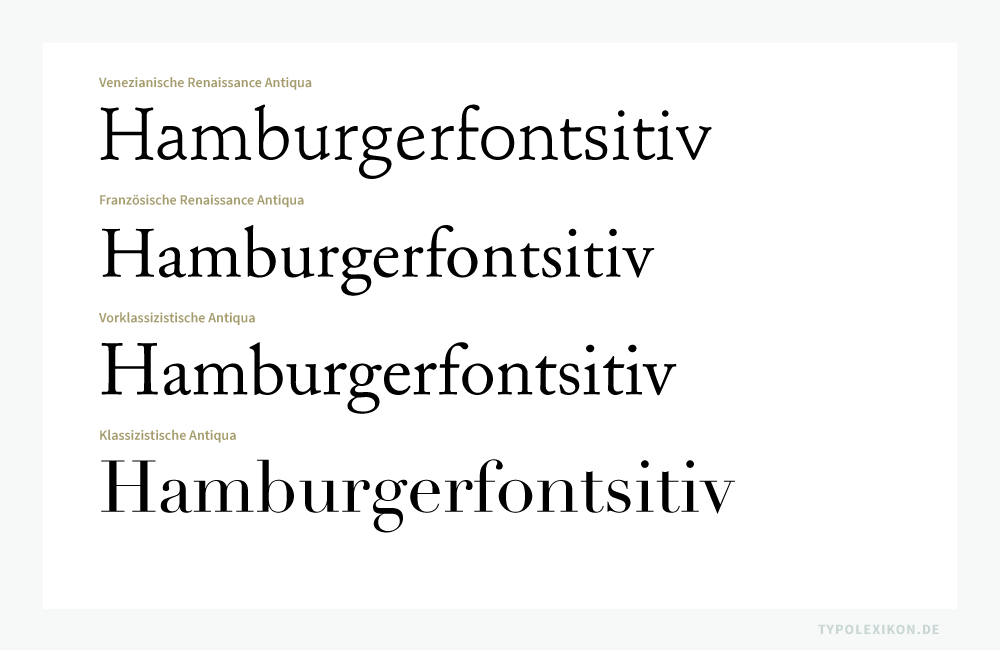
Schriftklassifikation
»Schriftklassifikation« ist ein Terminus aus der Typografie und der Paläografie. Sie dient dem Ordnen, dem Katalogisieren und der Pflege von Schriften in Schriftenbibliotheken sowie dem Studium von Schriften. Klassifikations- und Ordnungsmodelle optimieren spürbar typografische Gestaltungs- und Arbeitsprozesse, also den typografischen Workflow vom Entwurf bis zur Produktion.
Neben philologischen Klassifikationsmodellen existieren für Druckschriften römischen Ursprungs unterschiedliche typografische Klassifikationsmodelle, beispielsweise:
-
- die multinationale »Typeface Design Grouping according to AFI« nach ISO/IEC 9541 der International Organization for Standardization (letztes Update: 2012) 1)
- die deutsche »DIN 16518« für materielle Druckschriften im Bleisatz (letztes Update: 1964) 2)
- die deutsche »Matrix Beinert« von Wolfgang Beinert für Schriften im Electronic Publishing (letztes Update: 2018)
- die italienische »Classificazione Novarese« von Aldo Novarese für materielle Druckschriften im Bleisatz (letztes Update: 1957)
- die französische »Classification typografique de Vox-AtypI« von Maximilien Vox für Druckschriften (letztes Update: 1954)
- die englischen Typeface Classifications »British Standards« für materielle Druckschriften im Bleisatz (letztes Update: 1967)
Die Klassifikation von Druckschriften hat ihren Ursprung in den historischen Hilfswissenschaften Paläografie und Paläotypie. 3) Die jeweiligen Klassifikationsmodelle weisen in der Regel markante Unterschiede auf.
Die Eingruppierung einer Druckschrift, eines Screen Fonts bzw. Webfonts erfolgt in der Regel nach entsprechend nachvollziehbaren Merkmalen und wird jeweils durch Beispiele veranschaulicht, wobei die Klassifikationsmerkmale einer digitalen Schrift heute meist unkonkret sind und die Grenzen zwischen den Schriftarten und deren Nebengruppen fließend verlaufen.
Druck- und Screenschriften bzw. Fonts werden in der Regel je nach Ursprung in Schriftgattungen, Hauptschriftgruppen, Schriftuntergruppen (Schriftarten) und Schriftnebengruppen gegliedert. Des Weiteren stehen zum Aufbau einer Klassifikationsmatrix u.a. die Schriftbezeichnungen, Schriftschnitte (Schriftstile), das Figurenverzeichnis, die Schriftbibliothek, der Schriftgestalter bzw. Schriftschneider, das Entstehungsjahr, die Schrifttechnik, die Quelle und der Distributor zur Verfügung.
Beispiel eines Schriftklassifikationsmodells in Form der Matrix Beinert anhand einer Bauer Bodoni Roman von Linotype®:
| Taxonomie | Beispiel | |
|---|---|---|
| Schriftgattung: | Antiqua-Schriften | |
| Hauptschriftgruppe: | Antiqua (Serif) | |
| Schriftuntergruppe (Schriftart): | Klassizistische Antiqua | |
| Schriftnebengruppe: | Bodoni-Varianten | |
| Schriftbezeichnung: | Bauer Bodoni™ | |
| Schriftschnitt | Roman | |
| Schriftgestaltung Original: | Giambattista Bodoni | |
| Schriftgießerei Orginal: | Stamperia reale, Parma | |
| Schriftgestaltung Remake: | Heinrich Jost und Lois Höll, 1926/1927 | |
| Schriftgießerei Remake: | Bauersche Gießerei | |
| Lizenzgeber: | Bauer Types S.A. | |
| Vertrieb: | Linotype® | |
| Langer PostScript® Name: | BauerBodoniStd-Roman | |
| Katalognummer: | 16740074 | |
| Stand: | 1.2015 | |
Schrift ist nicht gleich Schrift
Bis zum Ende des materiellen Schriftsatzes in den 1970er Jahren konnten handelsübliche Schriften relativ einfach klassifiziert und in Gruppen eingeteilt werden. Dies ist seit dem optomechanischen Schriftsatz (Fotosatz) und insbesondere seit Beginn der digitalen Typografie (PostScript, TrueType, Bitmap, OTF-Technologie, Webfonts etc.) nicht mehr oder nur noch zum Teil möglich. Zu viele
-
- Repliken (erneute Ausführung eines bereits vorhandenen Originals durch den Schriftgestalter selbst),
- Remakes (spätere Nachbildungen einer bereits existierenden, aber nicht mehr am Markt verfügbaren Schrift, die sich streng am Original orientieren),
- Klone (1:1-Kopien einer Schrift),
- Formvarianten (abweichende Interpretationen einer bereits existierenden Schrift) 4) sowie
- Mischformen (Hybride aus unterschiedlichen Schriftuntergruppen und/oder Schriftnebengruppen)
existieren.
Einheitliche Formmerkmale – insbesondere bei Bildschirmschriften und Webfonts – sind kaum mehr konkret nachweisbar und es ist nahezu unmöglich geworden, Antiqua-Schriften kunstgeschichtlich zuzuordnen.
Typifikation
Wichtige typometrische Formmerkmale eines Buchstabens sind u.a. die Formgebung der Serifen, also die Serifenübergänge, Serifenseitenkanten und Serifenunterkanten (siehe Serife), die Form der Dachansätze, die Höhen und Proportionen der Oberlängen, Mittellängen und Unterlängen, die optische Achse der Rundformen sowie der Strichstärkenkontrast der Balken und Querbalken.
| ↑5 | Anmerkung: Der korrekte Begriff für Barock-Antiqua ist Vorklassizistische Antiqua. |
| ↑6 | Anmerkung: Verwirrende deutsche Begrifflichkeiten: In England gilt z.B. die Baskerville keineswegs als Barock-Antiqua, sondern als präviktorianische Antiqua. In der englischen und französischen Terminologie gibt es den Begriff »Barock-Antiqua« bzw. »Antiqua« nicht. In England bezeichnet man seit jeher die Antiqua als »roman« und ihre kursive Version als »italic«, die französische Typografie verwendet die Termini »romain« und »italique«. |